글로벌 콘텐츠 제작자 모이세요! K콘텐츠 인기에 해외 폰트를 찾는 수요가 늘어나고 있습니다. 그동안은 필요했던 해외 폰트를 구매하기가 번거로웠는데요. 산돌구름이 그 고민을 한 방에 해결해 드립니다! 이름만 들어도 ‘아, 거기!’ 하는 글로벌 유명 브랜드가 선택한 글로벌 폰트 4종을 소개합니다.
1. 더타입파운더스_Unpack
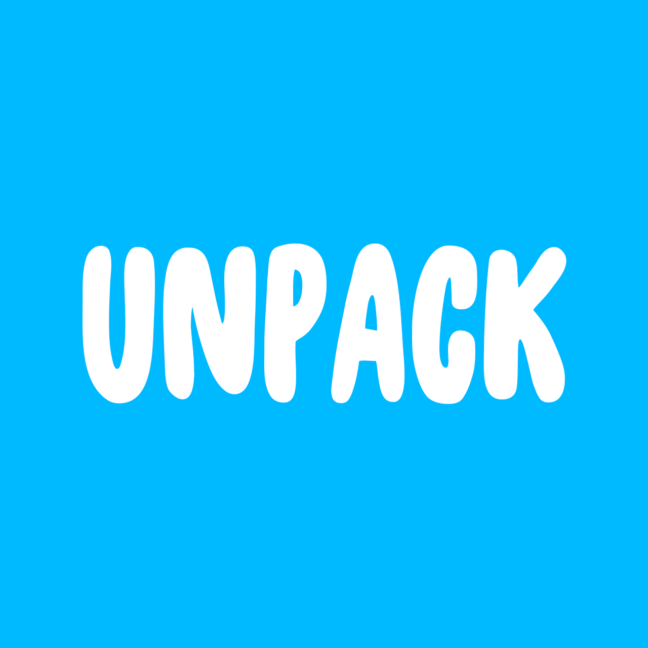
어릴 적 추억의 애니메이션, 요즘 다시 유행을 일으키고 있는 애니메이션 ‘파워퍼프걸’ 자막에 활용된 폰트 ‘Unpack’입니다. 동글동글한 테두리의 라운드 폰트로 발랄한 인상을 주면서, 독특한 심볼 문양도 제공하고 있으니 작업물에 유용하게 활용해보세요!
2. 폰트웍스_Yuruka’
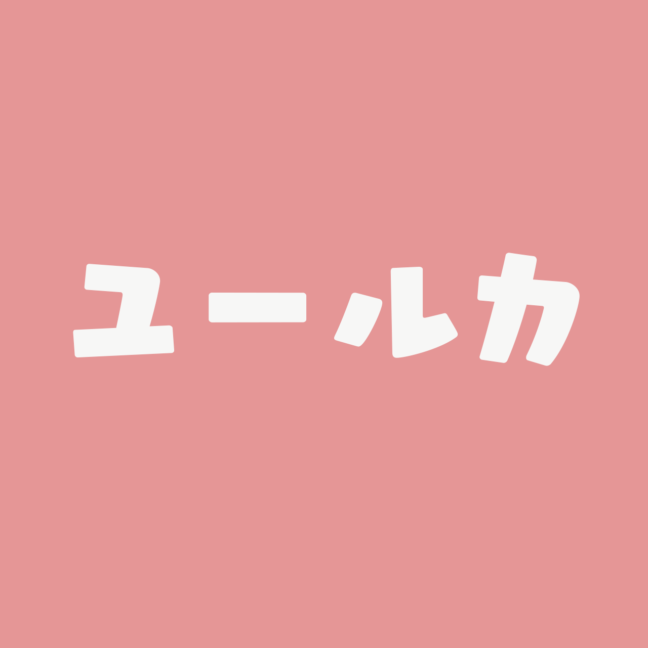
폰트를 잘 몰라도 게임을 좋아하는 사람이라면 익숙한 폰트! 닌텐도 게임 ‘모여봐요 동물의 숲’에 사용돼 유명해진 폰트웍스의 ‘Yuruka’입니다. 두꺼운 손글씨가 삐뚤빼뚤 쓰여 있어 어린이 글씨처럼 귀여운 인상을 가진 폰트입니다. 귀여운 캐릭터가 등장하는 포스터나 광고에 사용하여 아기자기한 느낌을 내보세요!
3. 디나모_Monument Grotesk
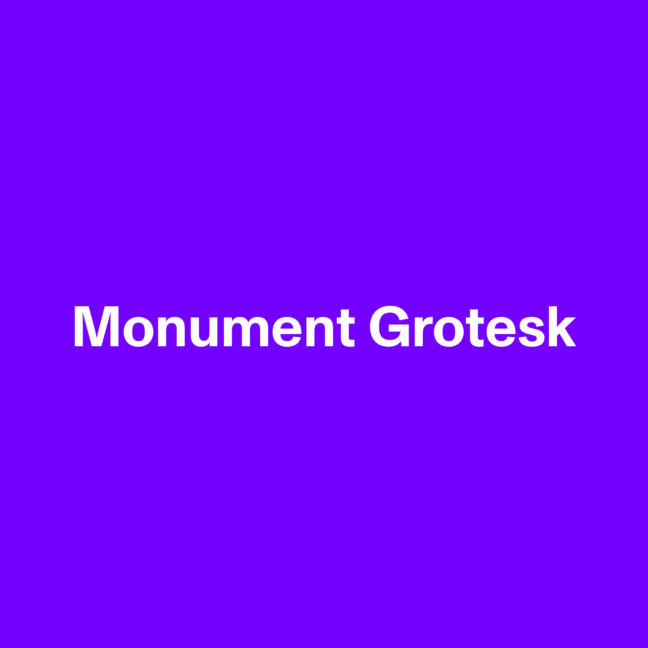
아디다스와 프라다의 협업 프로젝트, DAZED 잡지, 미국 플레이오프 전광판에 활용된 그 폰트. 글로벌 브랜드와 스포츠리그의 선택을 받는 디나모의 ‘Monument Grotesk’입니다. 깔끔하고 가독성이 좋은 산세리프 폰트로, 지면이나 웹사이트 어디에서도 활용성이 높습니다. 제목용으로는 두꺼운 Black과 Italic 스타일까지 제공하며, 본문용으로는 시리즈로 나온 ‘Monument Grotesk Mono’를 사용해보세요.
4. 티포텍_ History
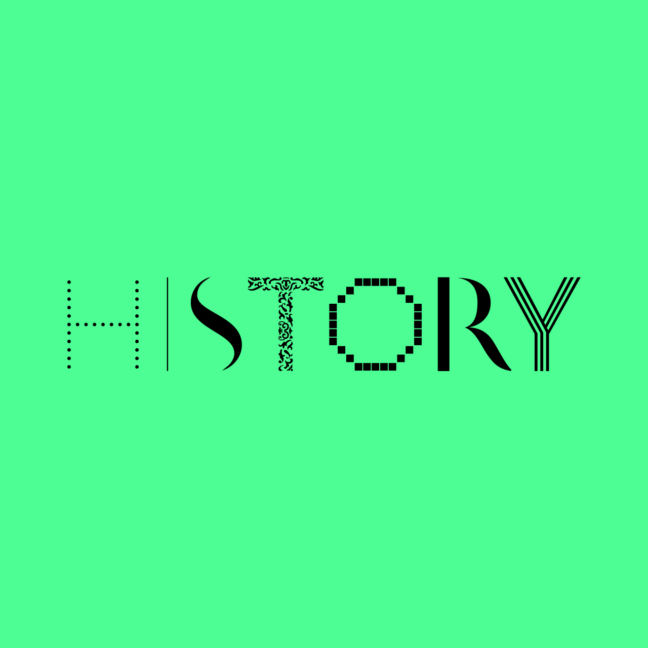
티포텍의 ‘History’는 타이포그래피의 진화 과정에서 영감을 받은 21개의 레이어로 이루어진 독특한 폰트 패밀리입니다. 아주 가는 뼈대만 있는 폰트부터, 장식적 요소로 꾸며진 폰트 등 다양한 스타일로 구성돼 있어 세계적인 박물관의 전시 포스터나 디자인 프로젝트에서 실험적인 형식으로 자주 사용되는 폰트입니다. 각 웨이트를 사용자가 원하는 방식으로 조합해 수천 가지 스타일로 사용할 수 있으니 여러분이 원하는 조합으로 나만의 독특한 디자인 작업물을 만들어보세요!